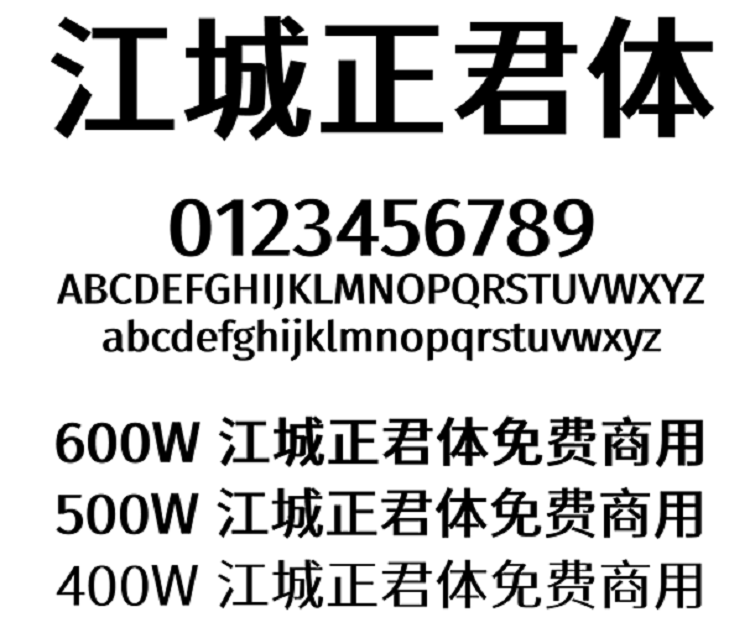
江城正君体是设计师刘鹏基于未来荧黑改造的一款免费商用黑体字体,它和江城正义体是姐妹篇。作者将原字体的笔画横向适当减细、竖向略微加粗,整体结构看起来修长清晰,既有黑体的稳重又具备宋体的挺拔。同时还优化了数字 4、7 及字母 K、k 的字形,提升美观度与识别性。
江城正君体覆盖简体中文(GB2312)、常用繁体、英文及数字符号,包含 3 种字重,可以满足不同的设计场景:
- 江城正君体 400W:常规字重,适合正文和一般普通标题。
- 江城正君体 500W:中等加粗,平衡可读性与视觉冲击力。
- 江城正君体 600W:最粗字重,适合突出的标题和 LOGO。
江城正君体 vs 江城正义体:
| 对比项 | 江城正君体 | 江城正义体 |
|---|
| 设计师 | 刘鹏 | 刘鹏 |
| 基础原型 | 未来荧黑 | 思源黑体 |
| 字重数量 | 3 种(Regular/Medium/Bold) | 5 种(更丰富) |
| 字形特征 | 窄长舒展,横向收紧、纵向拉长 | 方正常规,整体更宽厚 |
| 笔画特点 | 横细竖粗,对比适中 | 笔画粗细对比更夸张、更粗犷 |
| 整体风格 | 现代、科技、挺拔、干练 | 力量感强、醒目、硬朗 |
| 适用场景 | 标题、海报、新媒体、短视频字幕 | 大字标题、户外广告、强视觉排版 |